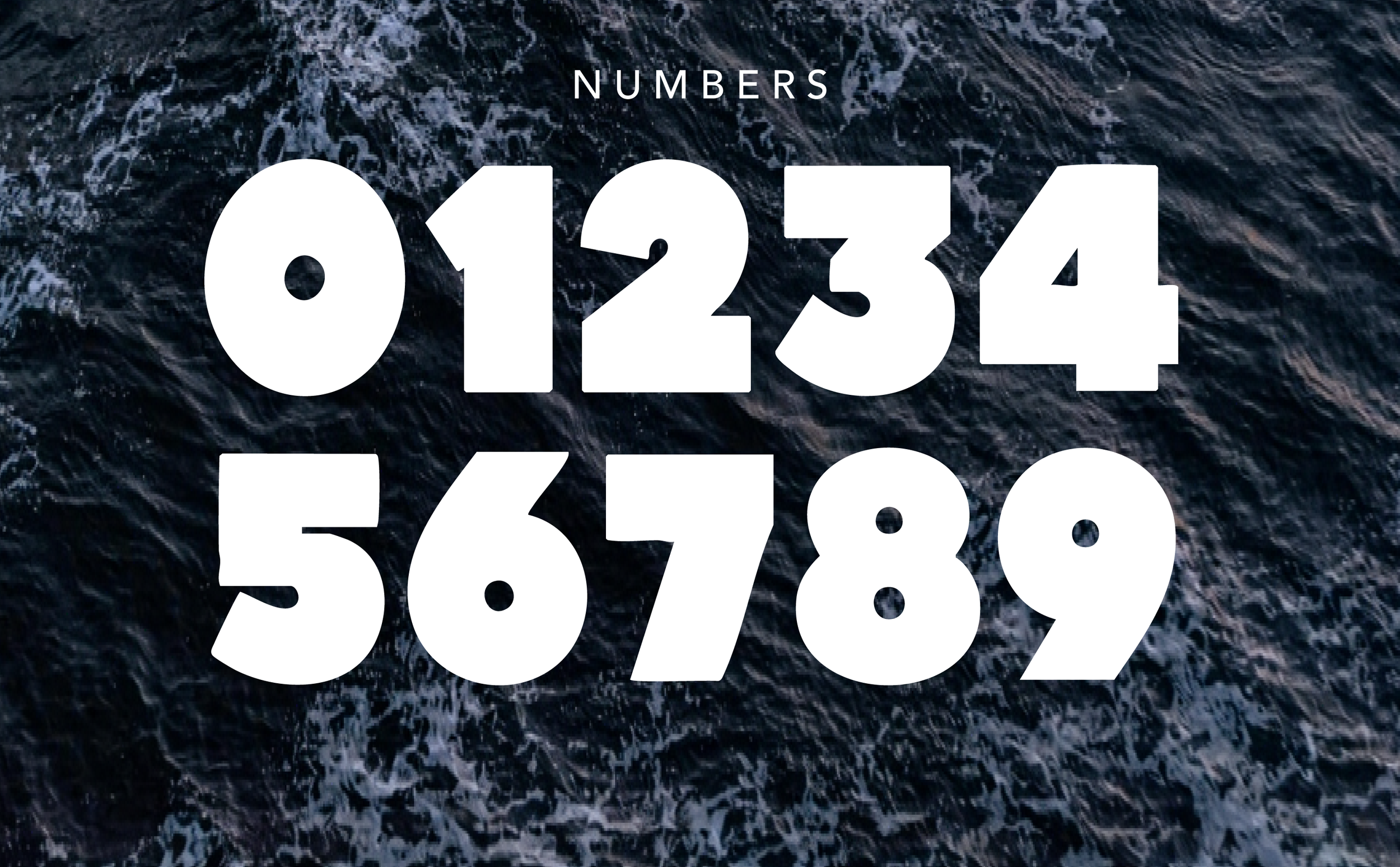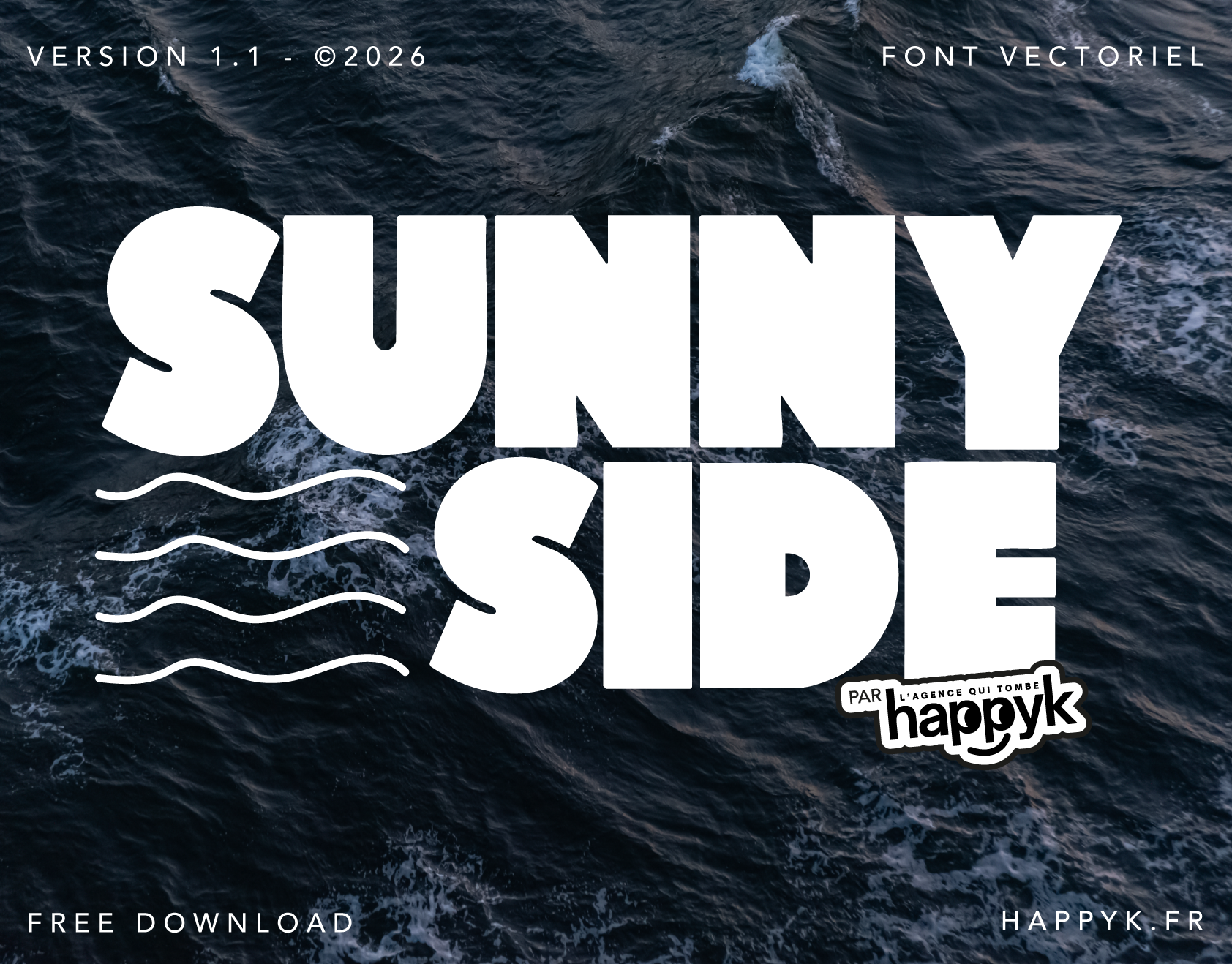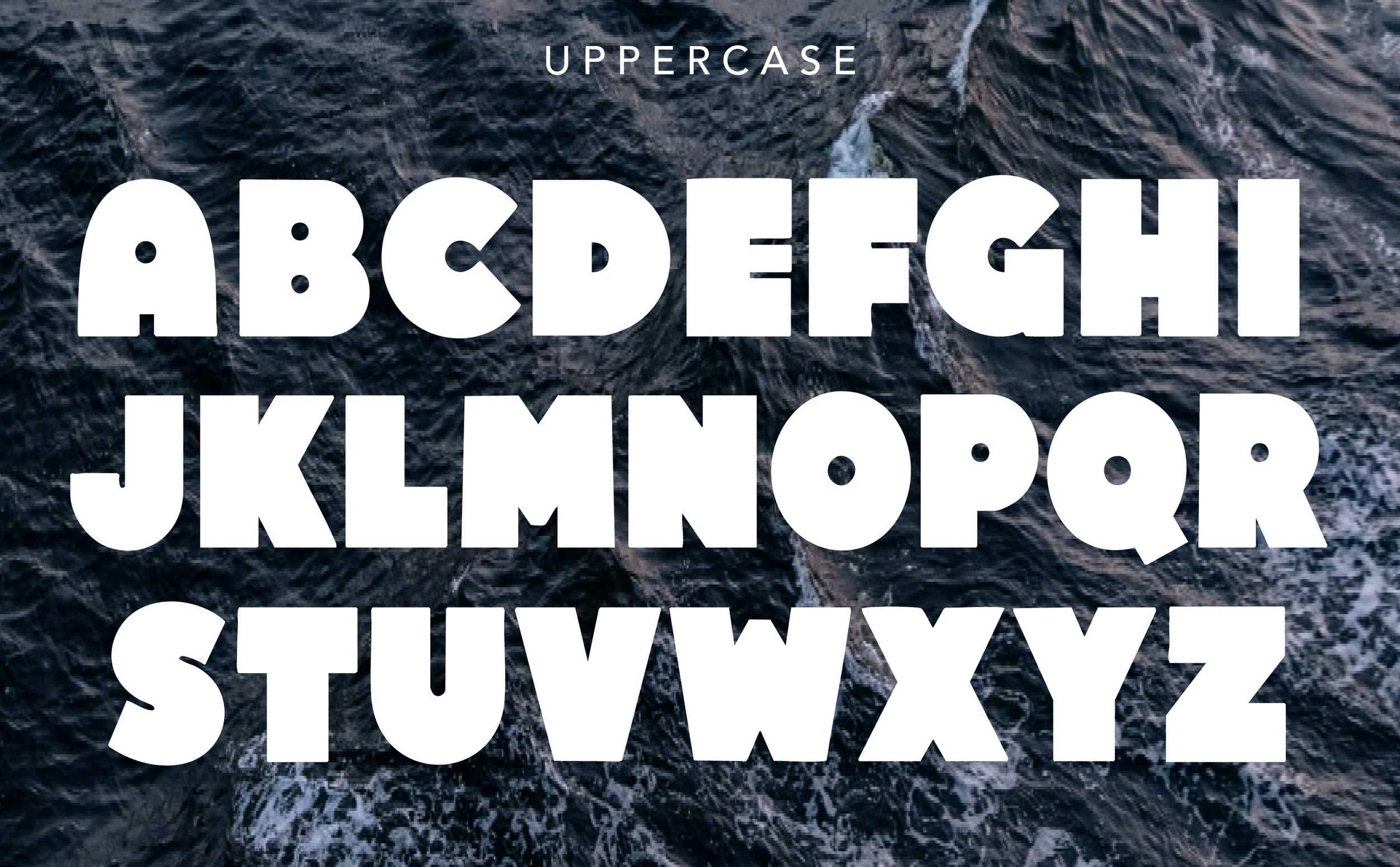
SUNNY_SIDE
Sunny Side
Une typo qui sent les embruns, les vacances et les terrasses en bord de mer.
Sunny Side est une police de caractères épaisse, solaire et pleine de bonne humeur. Avec ses formes généreuses et ses découpes inspirées du mouvement des vagues, elle apporte instantanément une touche estivale à n’importe quel projet.
Parfaite pour les identités de marque, restaurants, événements, affiches, packagings ou projets touristiques, elle a été pensée pour être lisible, mémorable et amusante.
Une typo qui regarde toujours du côté ensoleillé. 🌊☀️